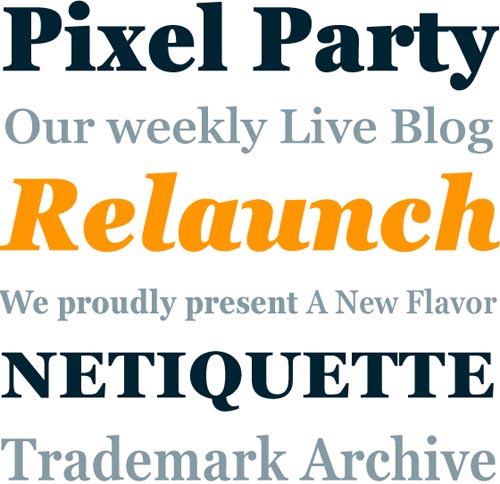
Die von Matthew Carter vor 15 Jahren entworfenen Schriften Georgia und Verdana wurden in Kooperation mit Monotype/Linotype sowie The Font Bureau ausgebaut und liegen nun als erweiterte Pro-Versionen mit je 20 Schnitten vor. Sie bieten mehr Strichstärken, eine größere Zeichenausstattung und erweiterte Sprachunterstützung. Beim Design der Schriften setzte Carter mit seinem Vorgehen Maßstäbe für die Bildschirmtypografie: ausgehend von der gerasterten Pixeldarstellung entwarf er die vektorisierten Buchstaben.
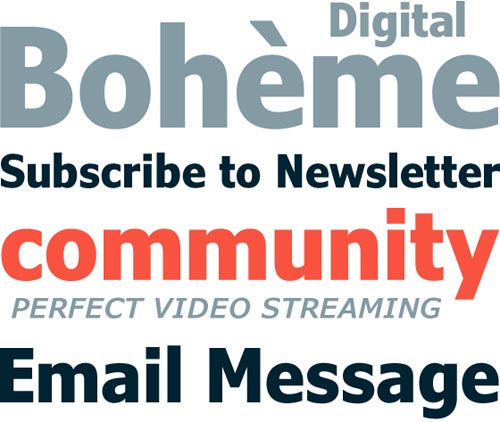
An den Pro-Versionen der Schriften hat Matthew Carter nun gemeinsam mit David Berlow (Font Bureau), Steve Matteson und Tom Rickner (Monotype Imaging) gearbeitet. Dabei wurden die Schriftfamilien (Regular und Bold) um die Strichstärken Light, Semibold und Black ergänzt, jeweils auch in Kursivvarianten. Neu hinzugekommen sind die für alle Strichstärken passenden Condensed-Schnitte.
Im Inneren der OpenType-Versionen »verstecken« sich Kapitälchen, Standardligaturen sowie Mediäval- und Versalziffern. Als Pro-Schriftfamilien unterstützen beide den pan-europäischen Sprachraum, verfügen also auch über griechische und kyrillische Zeichen.
ahhh. das gefällt mir sehr. das dürfte den umgang mit der verdana im web doch vereinfachen. schade, dass sie nicht in allen betriebssystemen vorliegen wird. das wäre doch mal ein guter schritt. die verdana black z.b. finde ich klasse. schön kompakt.
Welches Betriebssystem geht denn nicht Thomas? Mit plus Webtype sollte doch so ziemlich alles abgedeckt sein. (Small Caps und verschiedene Ziffernvarianten folgen als extra fonts für browser, die keine OpenType-features unterstützen, siehe Asterisk.)
genau indra, die möglichkeiten an sich aufpolieren. webfonts sind immer noch, schwierig … hinting und co. stellen für echte professionelle anwendungen immer noch oft ein hindernis dar.
Die Verdana bleibt für mich weiterhin unsexy ;-) Da gibt es meiner Meinung nach schönere Schmuckstücke.
Die PRO-Version der Georgia gefällt! Damit ist ein hochwertiges Corporate Design möglich und trotzdem bleibt die »normale« Georgia als Backup, wenn Schriften einbetten mal nicht möglich ist. Nun, die Verdana bleibt in großen Größen leider weiterhin nicht so toll …
Oder vielleicht habe ich Dich doch nicht richtig verstanden, Thomas? Du hättest gerne, dass die beiden Pakete mit allen Betriebssystemen ausgeliefert werden, oder? Das würde sehr sehr teuer werden.
Was ist denn an diesen webfonts schwierig? Gerade das hinting ist hier doch sensationell professionell.
indra: ja bei diesen schriften. bei vielen fonts von diversen anbietern eben nicht. cleartypehinting reicht leider nicht aus. es sind noch zu viele alte rechner unterwegs.
die frage ist ja, was ist schlimmer? eine nur bedingt erträgliche vielfalt oder eine vernünftig aussehende »monokultur« auf allen systemen …